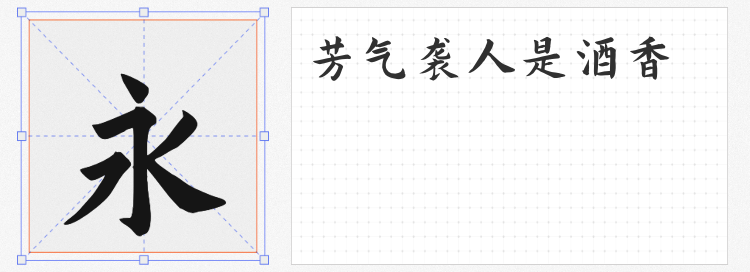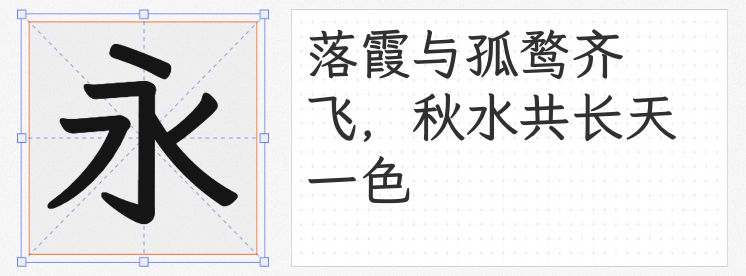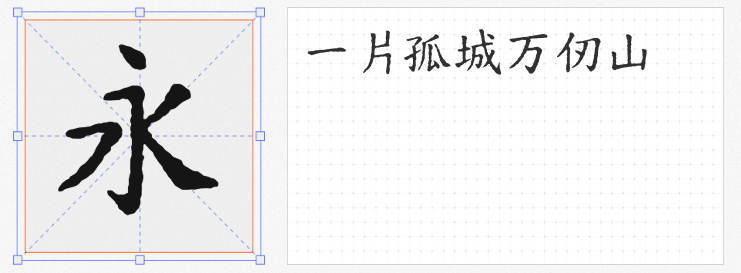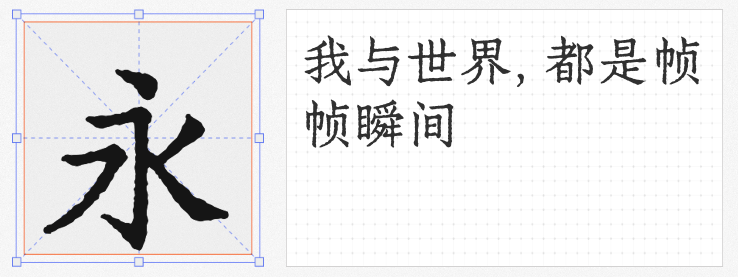
在平面设计与数字内容创作中,书法字体是传递文化底蕴与艺术美感的核心元素。本文精选四款免费可商用的书法字体,它们均以开源字体为基础优化,兼具实用性与艺术性,尤其适合文化海报、品牌包装、古籍排版等场景。
基于开源字体“演示秋鸿楷”拓展的寒蝉书体·春秋 秋鸿,以“人文、古典、复古”为风格定位,在保留传统楷书骨架的基础上,优化了西文字符与数字的均衡性,解决了部分汉字忽高忽低的问题,并调整字偶距以提升排版流畅度。其新增的“啰、瞭、舖”等一级规范通用字,填补了基础字库的空白。这款字体在古籍封面、文化展陈设计中表现尤为突出,例如《兰亭集序》的排版中,其温润的笔画与古雅的韵味相得益彰。
霞鹜文楷 GB Medium以日本FONTWORKS的Klee One为灵感,通过增补与修改字形,严格遵循《通用规范汉字表》标准,保留了印刷体的“直点”“断笔”特征,同时弱化日式风格,强化国标规范。其SemiBold字重设计使电子屏幕阅读更舒适,支持8105个规范汉字,覆盖现代汉语常用需求。在教育类书籍、文化纪录片字幕中,这款字体既能体现严谨性,又因仿宋与楷体的融合而兼具灵动感。
寒蝉活仿宋Regular通过模拟轻度油墨溢出效果,赋予字体复古的“做旧”质感。基于朱雀仿宋与Simonetta修改的它,新增英文适配与字符标点,并优化竖向排版。尽管字符集因斑驳效果有所精简,但优先保留的网络常用简繁字已能满足多数设计需求。在茶饮品牌包装、手工艺品宣传中,其驳杂的曲线与古朴的纹理能瞬间营造出时光沉淀的氛围。
以全字库正楷为基底的寒蝉活楷体,通过斑驳的纹理处理与字形修正,打造出独特的“旧书页”视觉效果。其GB2312标准字符集覆盖基础汉字需求,均衡的排版与复古风格使其成为文化类PPT、传统节庆海报的优选。例如在中秋主题设计中,其略带沧桑感的笔画与圆月、灯笼等元素形成时空对话,强化文化叙事。